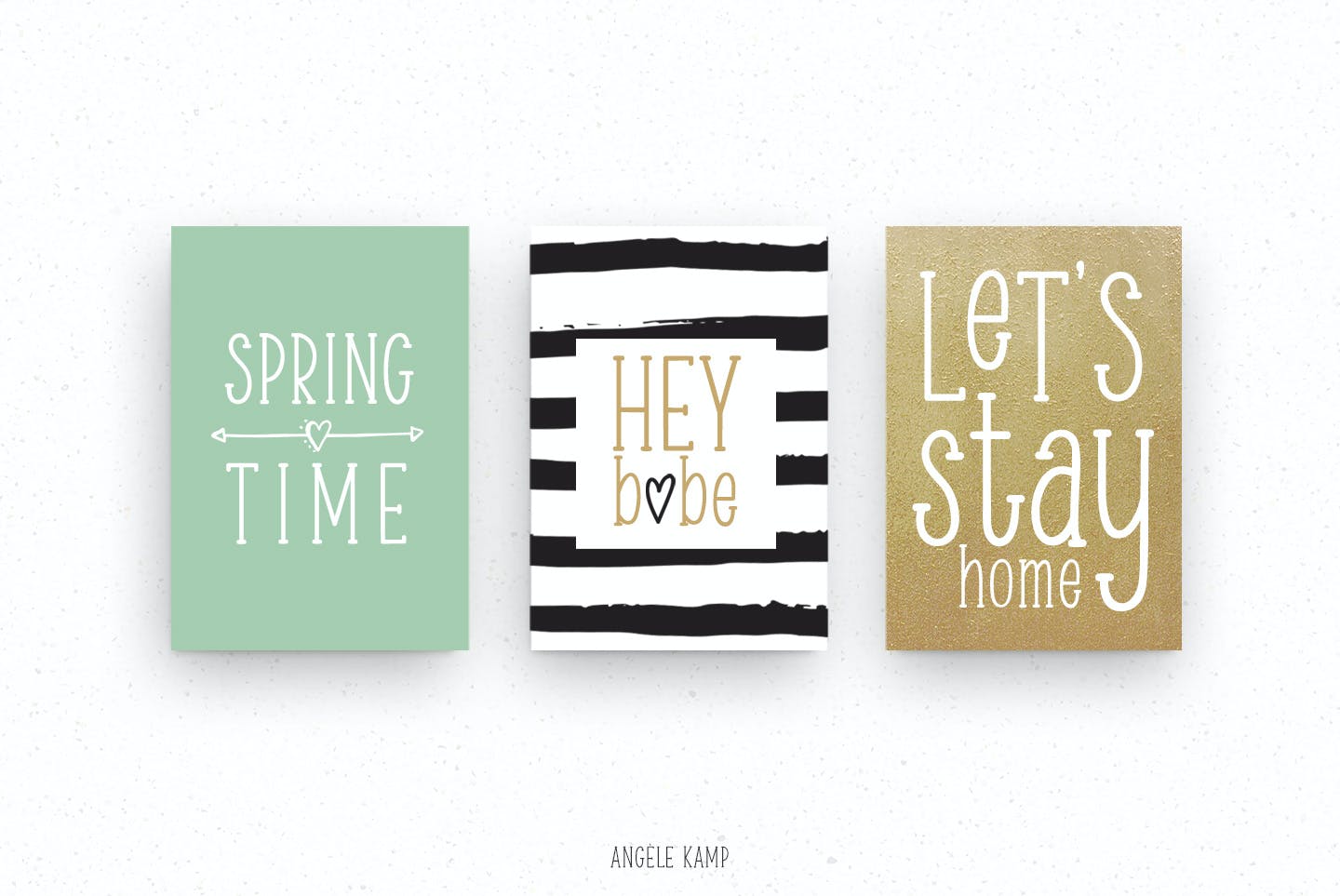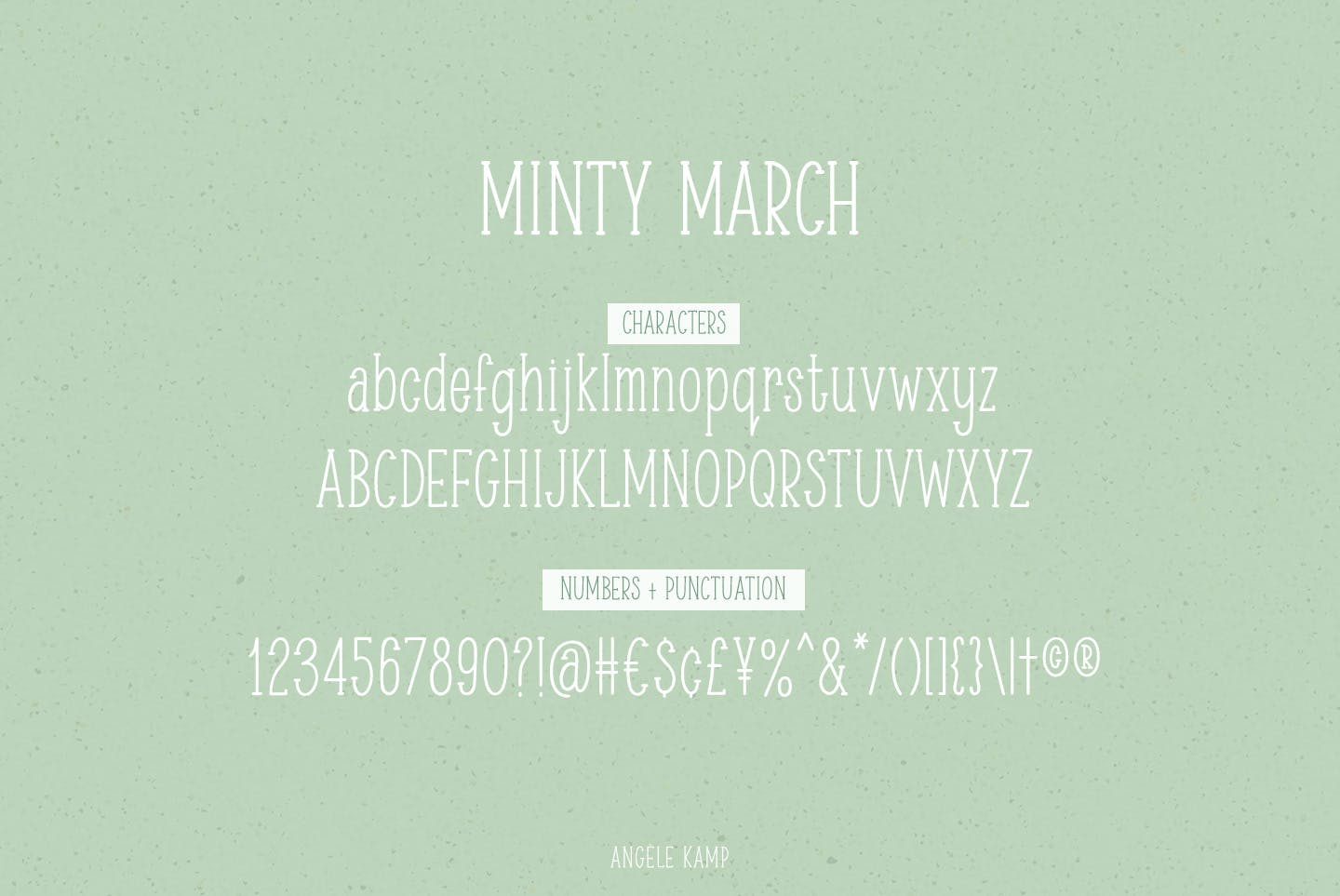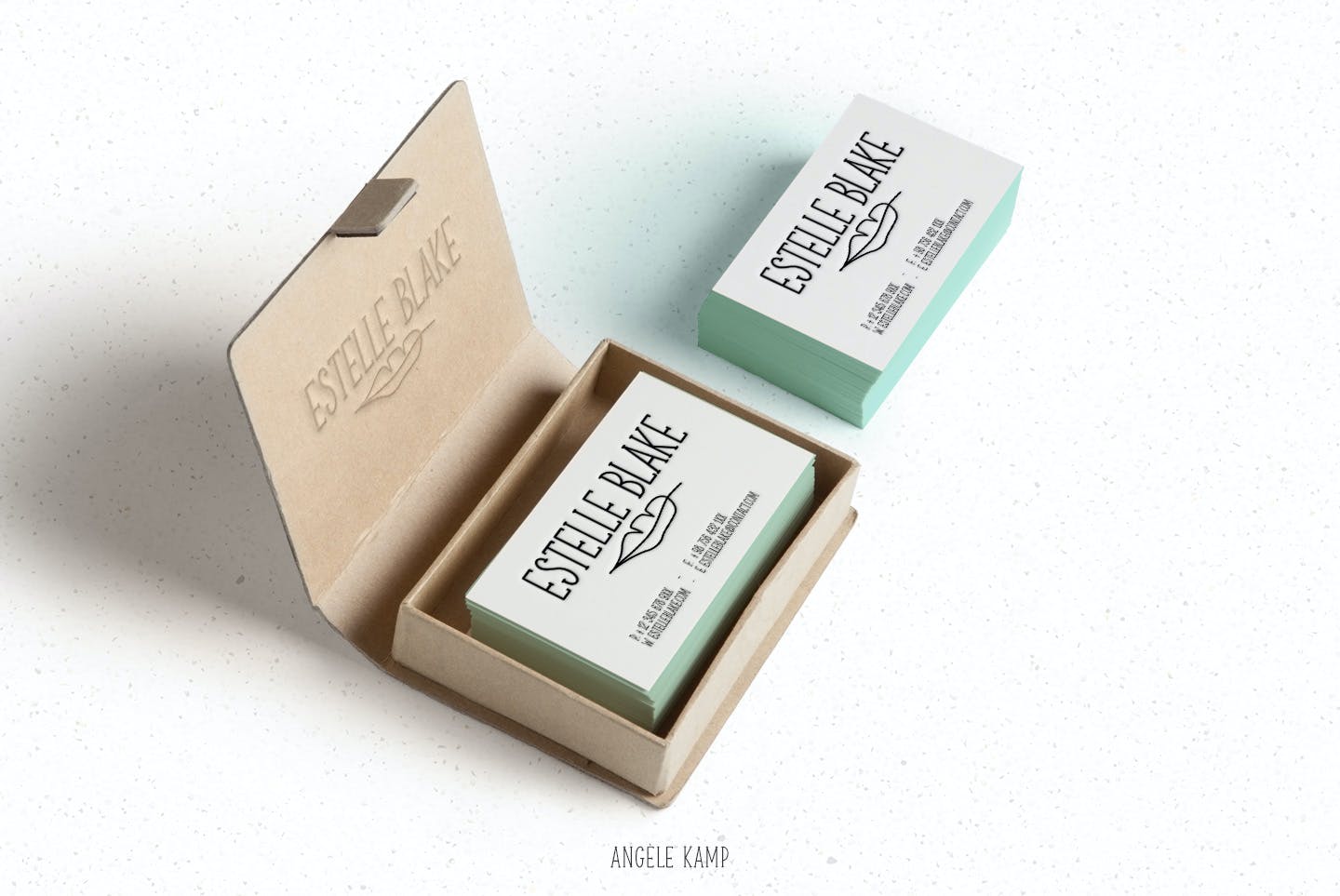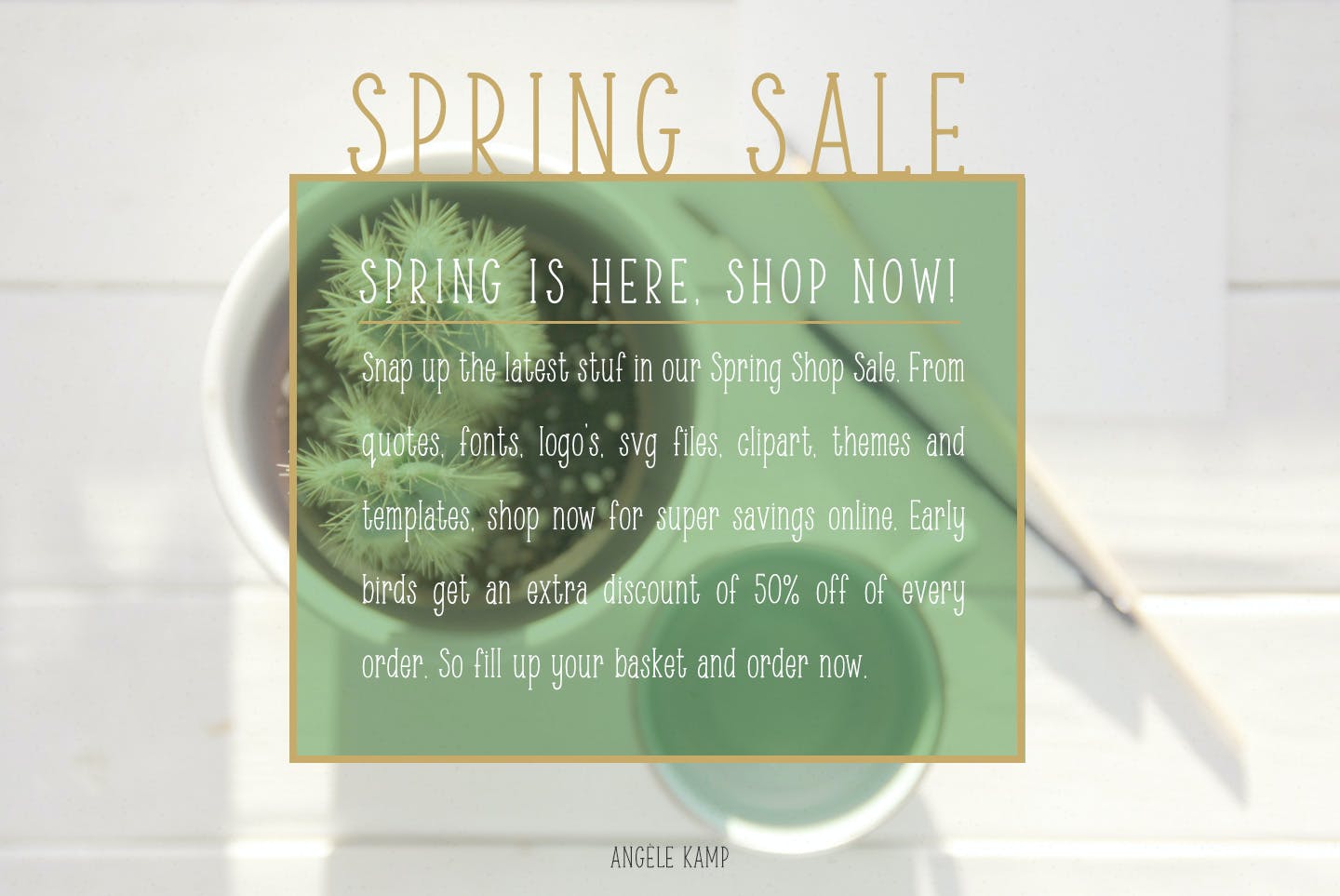
فونت مینتی مارچ یک فونت دستنویس جذاب است که برای طراحی کارتها، دعوتنامهها، لوگوها، دعوتنامههای تولد و موارد دیگر بسیار مناسب است. این فونت با طراحی باریک و سر سریف، به خوبی با فونتهای اسکریپت ترکیب میشود.
شامل چه مواردی است: فونت مینتی مارچ شامل کاراکترهای استاندارد، حروف کوچک، حروف بزرگ، اعداد، علائم نگارشی، لیگاتورها و کاراکترهای بینالمللی میباشد.